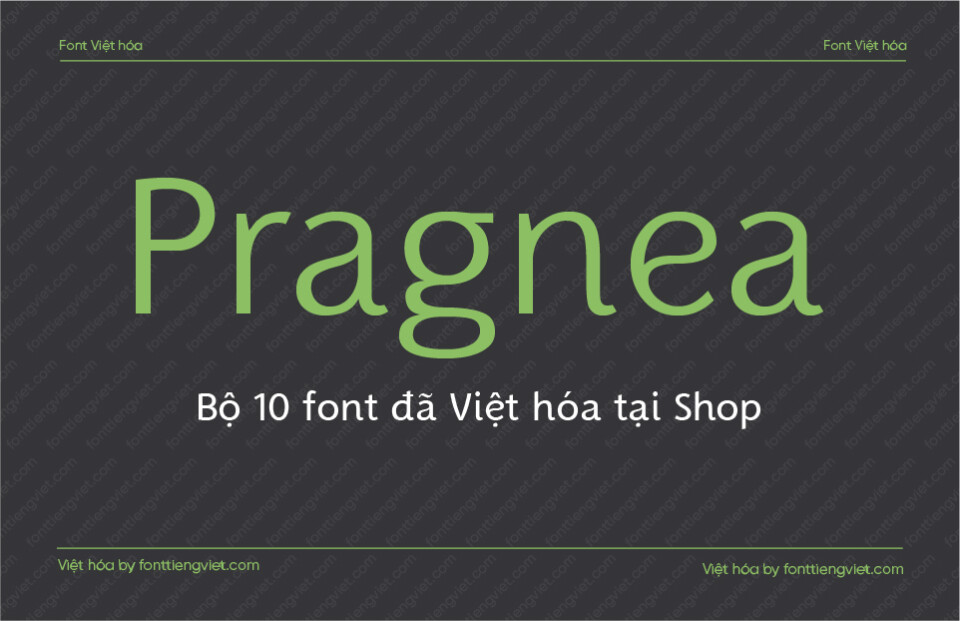
Font Việt hóa 1FTV VIP Pragnea Regular
Giới thiệu về sức hút của Font Việt hóa 1FTV VIP Pragnea Regular
Trong thế giới sáng tạo nội dung hiện nay, việc lựa chọn một phông chữ phù hợp không chỉ giúp truyền tải thông điệp mà còn khẳng định phong cách cá nhân độc đáo. Font Việt hóa 1FTV VIP Pragnea Regular nổi lên như một hiện tượng trong cộng đồng thiết kế nhờ sự kết hợp hoàn hảo giữa nét cổ điển và hơi thở hiện đại. Đối với các bạn học sinh và giáo viên, việc tìm kiếm một Font Miễn Phí nhưng vẫn đảm bảo tính thẩm mỹ cao để trình bày bài báo tường, slide thuyết trình hay các ấn phẩm học đường là điều vô cùng cần thiết. Phông chữ này mang đến một cảm giác thanh lịch, chuyên nghiệp giúp mọi nội dung văn bản trở nên cuốn hút và dễ tiếp cận hơn với người xem ngay từ cái nhìn đầu tiên.
Những đặc điểm nổi bật của bộ Font Việt hóa 1FTV VIP Pragnea Regular
Thiết kế tinh tế và độ tương phản hoàn hảo
Font Việt hóa 1FTV VIP Pragnea Regular sở hữu các đường nét thanh mảnh nhưng vô cùng dứt khoát. Cấu trúc của phông chữ này được tối ưu hóa để giữ được độ rõ nét ngay cả khi hiển thị ở kích thước nhỏ hoặc in ấn trên các khổ lớn như banner, poster. Sự cân bằng giữa các khoảng trắng và nét chữ giúp mắt người đọc không bị mỏi, điều này đặc biệt quan trọng trong môi trường giáo dục khi các bài giảng cần sự tập trung cao độ. Pragnea Regular không chỉ đơn thuần là một công cụ viết chữ mà còn là một tác phẩm nghệ thuật giúp nâng tầm giá trị cho mọi bản thiết kế đồ họa.
Khả năng tương thích và tối ưu hóa tiếng Việt
Điểm mạnh lớn nhất của Font Việt hóa 1FTV VIP Pragnea Regular chính là bộ dấu tiếng Việt được trau chuốt tỉ mỉ. Khác với nhiều phông chữ nước ngoài khi gõ tiếng Việt thường bị lỗi font hoặc dấu đặt không đúng vị trí, phiên bản 1FTV VIP này đã xử lý triệt để mọi khuyết điểm đó. Các dấu thanh như huyền, sắc, hỏi, ngã, nặng được thiết kế hài hòa với chữ cái chính, tạo nên một tổng thể đồng nhất và đẹp mắt. Điều này giúp các bạn học sinh dễ dàng sử dụng trong các phần mềm soạn thảo văn bản hay thiết kế như Canva, Photoshop và PowerPoint mà không gặp bất kỳ trở ngại nào về kỹ thuật.
Ứng dụng thực tế của Font Việt hóa 1FTV VIP Pragnea Regular trong học tập
Trình bày slide bài giảng và tiểu luận
Một bài thuyết trình ấn tượng bắt đầu từ hình ảnh và phông chữ. Sử dụng Font Việt hóa 1FTV VIP Pragnea Regular cho các tiêu đề chính sẽ tạo ra điểm nhấn mạnh mẽ, giúp thầy cô và bạn bè dễ dàng theo dõi nội dung. Bên cạnh đó, phông chữ này còn rất phù hợp để in ấn các bìa tiểu luận, báo cáo thực tập, mang lại vẻ ngoài chỉn chu và nghiêm túc. Với phong cách chuyên nghiệp, Pragnea giúp các sản phẩm học thuật trở nên giá trị hơn trong mắt người đánh giá.
Thiết kế thiệp mời và kỷ yếu lớp
Mùa chia tay hay các dịp lễ hội tại trường là lúc cần đến sự sáng tạo. Font Việt hóa 1FTV VIP Pragnea Regular là lựa chọn tuyệt vời cho các mẫu thiệp mời họp lớp, chứng chỉ khen thưởng hay thiết kế trang bìa kỷ yếu. Sự thanh thoát của nó gợi lên những kỷ niệm đẹp đẽ và sự trân trọng. Việc sử dụng phông chữ này giúp các sản phẩm in ấn mang đậm dấu ấn cá nhân và tình cảm của lứa tuổi học trò hồn nhiên.
Kết luận về bộ Font Việt hóa 1FTV VIP Pragnea Regular
Có thể khẳng định rằng, việc sở hữu một bộ phông chữ chất lượng như Pragnea Regular sẽ giúp hành trình sáng tạo của bạn trở nên thú vị và hiệu quả hơn. Với tính ứng dụng cao và vẻ đẹp vượt thời gian, đây chắc chắn là lựa chọn không thể bỏ qua cho những ai yêu thích sự tinh tế. Hãy truy cập ngay để tải về Font Miễn Phí, Font Việt Hóa, Font Việt hóa 1FTV VIP Pragnea Regular và bắt đầu làm mới các dự án thiết kế của mình ngay hôm nay. Hy vọng bộ font này sẽ trở thành người bạn đồng hành đắc lực trên con đường học tập và sáng tạo của các bạn.